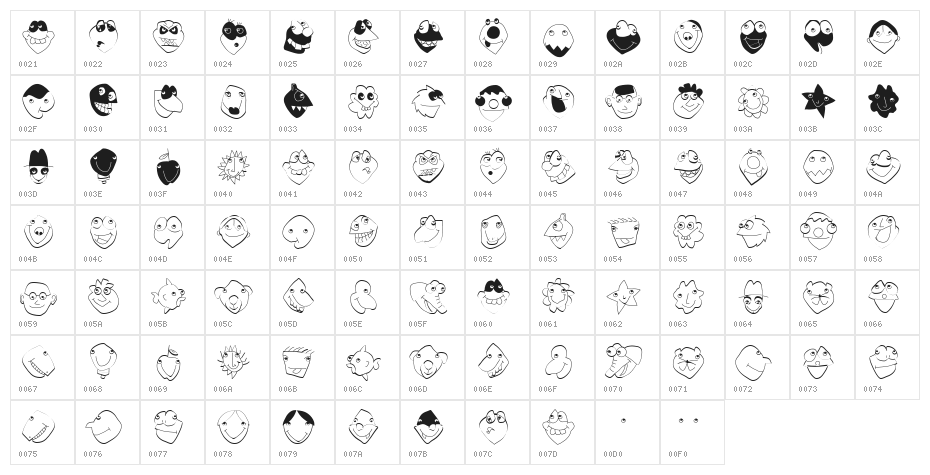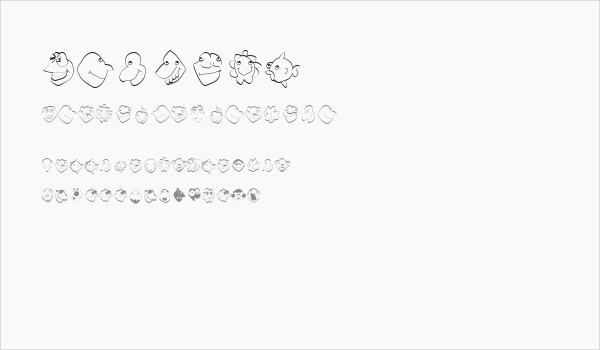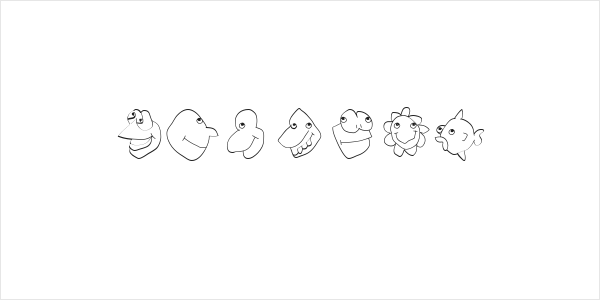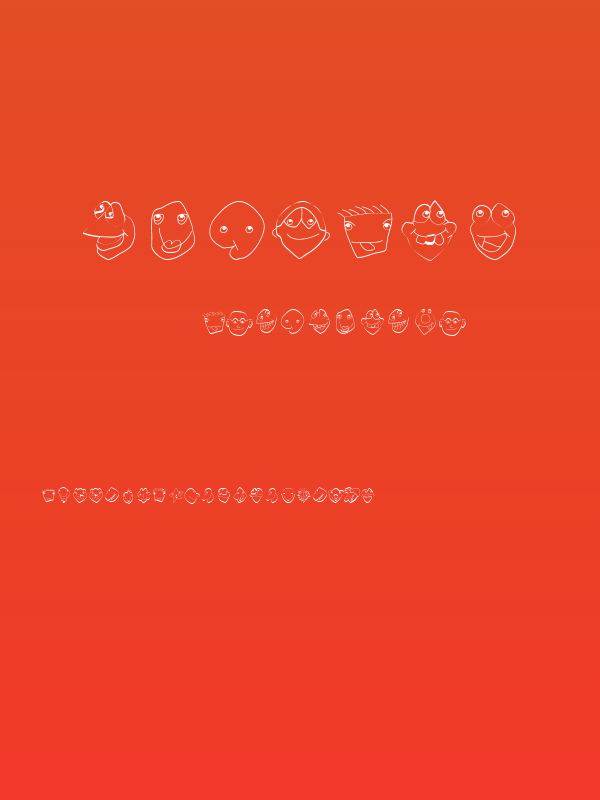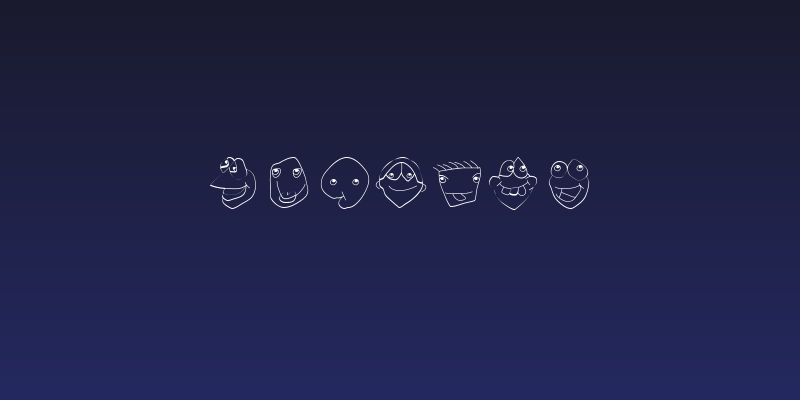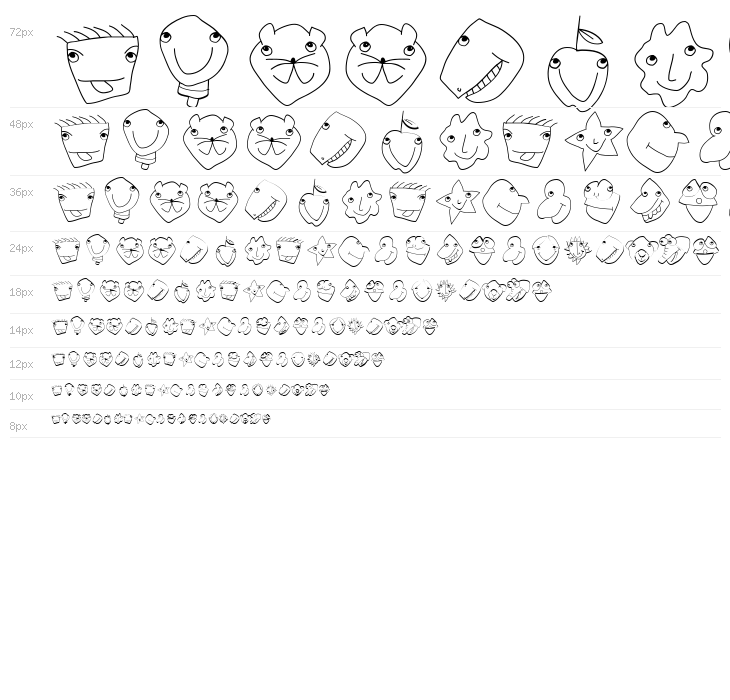
Frontal Font
| 整体风格 | Whimsical, Playful, Decorative |
| 使用场景 | Headlines, Logos, Posters, Themed graphics |
| 推荐项目 | Children's books, comic titles, party invitations, playful branding, educational materials. |